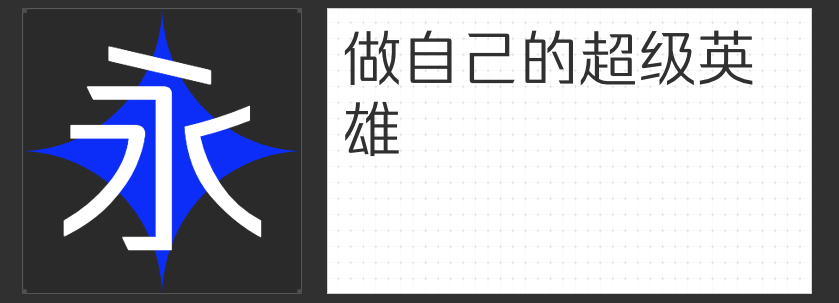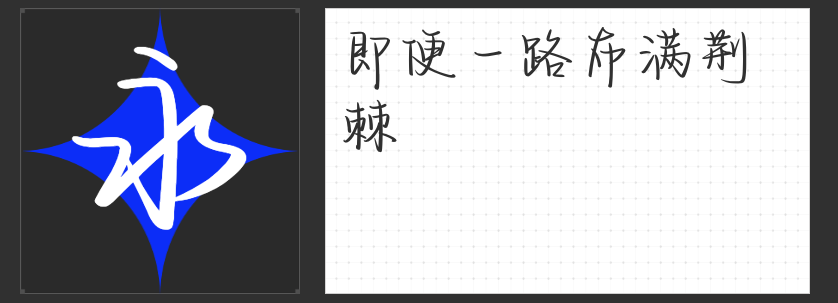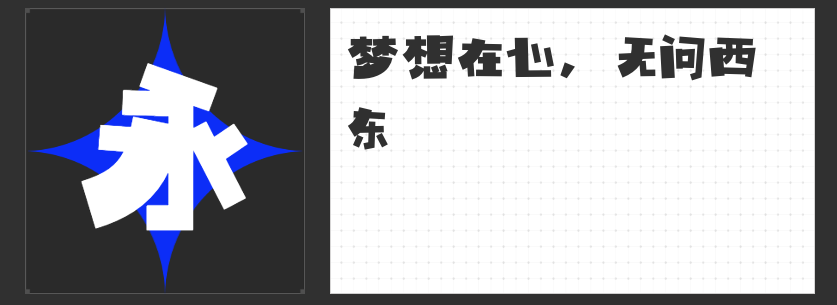
浪漫与艺术的交织:四款精选字体打造乙女游戏设计
在乙女游戏中,UI设计不仅关乎美观,更是情感体验的重要组成部分。好的字体选择能够增强游戏氛围,提升玩家沉浸感。今天,我们将为您推荐四款适合用于乙女游戏UI设计的字体。这些字体各具特色,能够为不同的游戏场景带来独特的视觉效果。
1. 励字超级勇士简 常规 —— 游戏界面的常规字体
“励字超级勇士简 常规”是一款既有着严谨结构、又兼具优雅的黑体。字重常规,字体粗细规则符合常规黑体,是一款适合阅读的字体。在乙女游戏中,玩家需要阅读大量的对话和剧情文本,因此选择一款易于阅读且具有亲和力的字体至关重要。“励字超级勇士简 常规”以其简洁明快的风格,非常适合用于整个系统的常规字体,如菜单、选项、提示等,确保玩家在享受游戏的过程中不会感到疲劳。
2. 造字侠热辣隶简 —— 古风与复古的完美呈现
“造字侠热辣隶简”是一款结合了传统隶书特点与现代设计元素的创意隶书。这种字体非常适合用于游戏内古风、复古、庄严风格活动的标题字体,如古代宫廷、武侠世界等场景。它线条流畅、笔画饱满,给人以强烈的复古感,能够为活动增添一份庄重与神秘的气息,使玩家仿佛置身于另一个时空之中,享受一段穿越之旅。
3. 万人字造拾梦简 超级黑 —— 萌动人心的创意字体
“万人字造拾梦简 超级黑”是一款字面多变、结构灵活、偏手写感的创意字体。这种字体非常适合用于游戏内一些风格可爱的活动的海报跟宣传使用,如萌宠专题、恋爱节日专题、儿童节专题等活动。其手写感强烈,字形可爱,能够唤起玩家心中的童真与甜蜜,营造轻松愉悦的游戏氛围,让玩家在游戏中感受到更多的乐趣与温暖。
4. 字圈也字专辑封面体 —— 角色个性的体现
说到游戏内活动设计的字体,手写体是必不可少的。“字圈也字专辑封面体”是一款风格端正的手写字体,除了用于活动平面设计,还可以当做角色的手写体。在乙女游戏中,角色之间的互动是核心体验之一。使用这种字体为角色设计专属的手写体,不仅能够展现角色的个性,还能增加玩家对角色的好感度,使角色更加立体和真实。
字体虽小,却能在游戏UI设计中发挥巨大的作用。上述四款字体各具特色,能够满足不同游戏场景的需求,帮助设计师们更好地表达游戏的情感与氛围。希望能在您在设计乙女游戏的UI时,能够从这些字体里找到最适合的那一款,为玩家带来一场视觉与情感的双重盛宴。